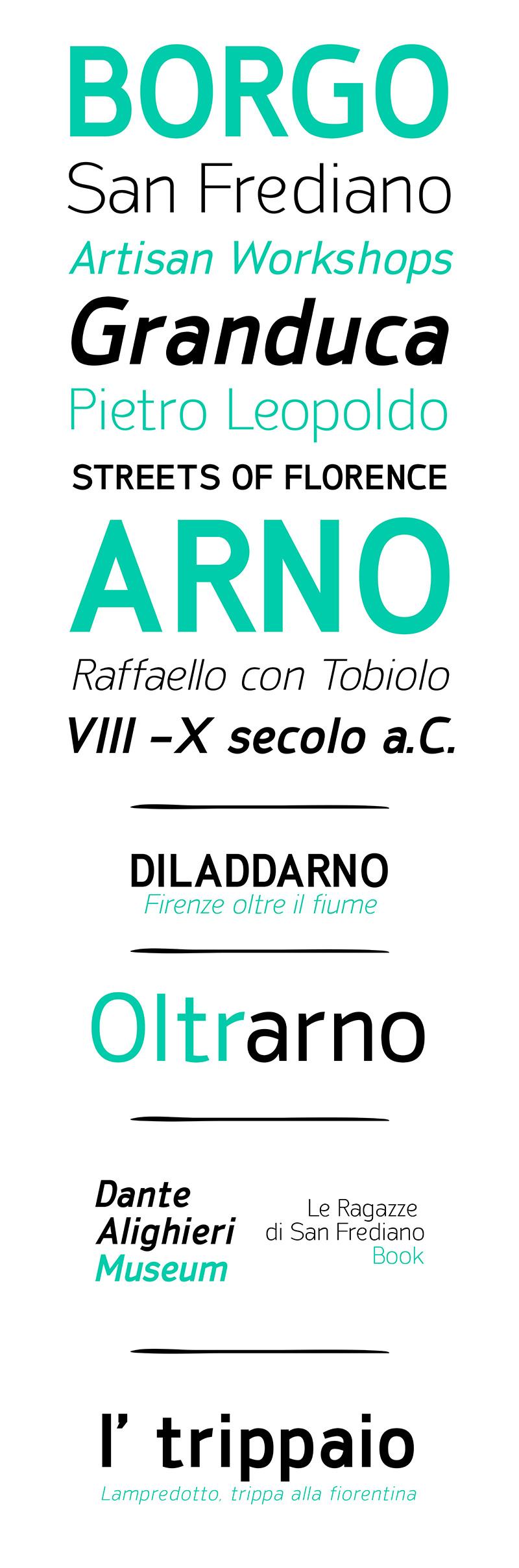
San Frediano Font Family
A San Frediano é uma tipografia Geometric Sans Serif inspirada no famoso bairro florentino onde está localizado o Studio Monocromo. Essa fonte abriga um grande número de detalhes sutis nas formas que, quando ampliadas, parecem esconder surpresas, muito como as ruas do bairro revelam intrigas em cada curva e ângulo. A diferença entre a altura das letras maiúsculas e minúsculas faz dela uma ótima fonte para web, perfeitamente adequada tanto no design gráfico quanto no uso de tipo. Ela é útil como fonte de destaque ou texto para o headline de jornais, as marcas publicitárias, a identidade corporativa e muito mais. A San Frediano oferece uma variedade incrível de opções para designers que buscam um estilo simples e limpo sem perder em elegância.